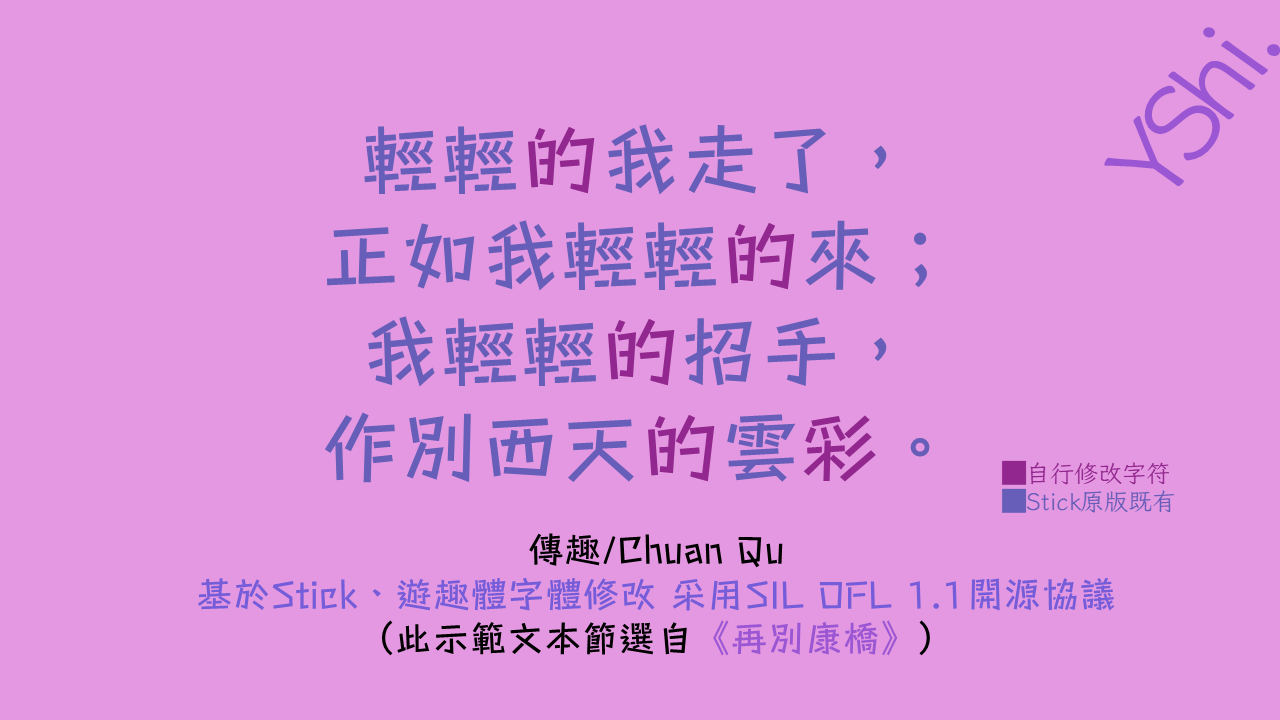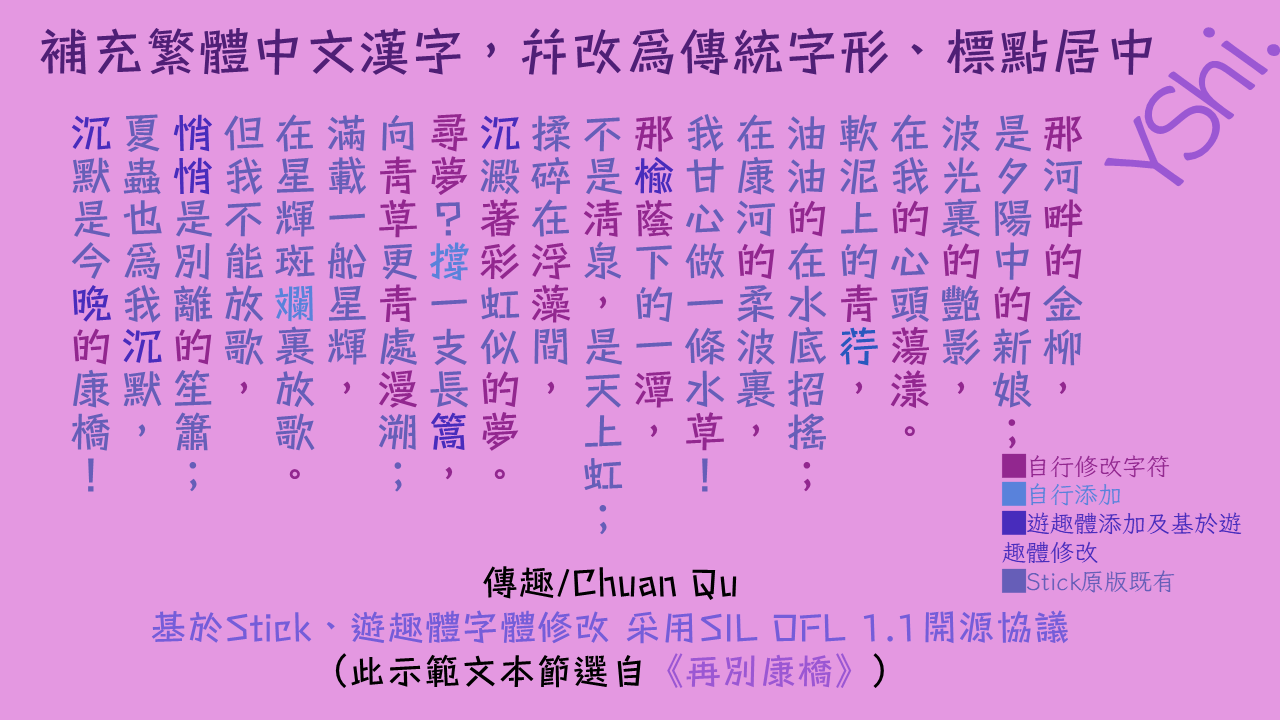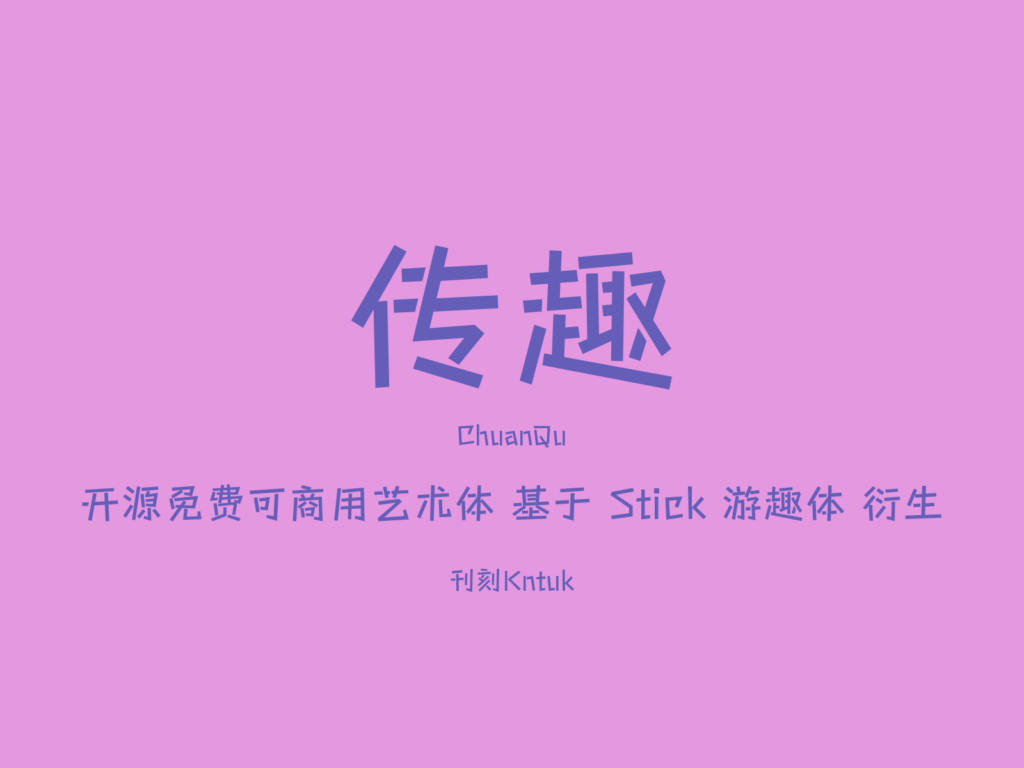
这是一款充满趣味的开源中文字体,其创意灵感源自经典的英文字体 Stick 与国内广受欢迎的中文字体「游趣体」。这款字体在设计和衍生过程中,特别注重融入旧字形元素,使得整体字形散发出一种既俏皮可爱,又带有几分复古韵味的独特风格。Stick 字体最初以其笔直、简洁的线条设计而闻名,这种模仿笔杆形态的直线条,赋予了字体一种天真调皮的性格,同时也营造出一种宁静的田园诗意感,仿佛能让人联想到手写涂鸦或乡村生活的闲适氛围。 由于原版的 Stick 字体主要针对拉丁字母设计,支持的汉字字形数量非常有限,难以满足日常中文书写、排版和设计工作的实际需求。为了解决这一问题,国内的设计师们创作了简体中文版的「游趣体」,极大地扩展了字体的字符集。然而,「游趣体」主要基于现代简化字形,对于追求传统书写美感和特定设计风格的爱好者而言,仍有所缺憾。 因此,出于对旧字形美感的欣赏和对完整字体功能的需求,我发起了这个开源项目。这个项目的核心目标,正是将「游趣体」现有的可爱风格与旧字形进行深度融合。我不仅为字体补充了大量的繁体汉字,使其能够同时适用于简体中文和繁体中文环境,更重要的是,我将许多字形的细节进行了调整,改用更接近传承字形或旧字形的写法,例如保留一些传统笔画结构和部件写法。这样做的目的,是希望创造出一款既能满足现代设计中追求活泼、可爱视觉效果的需求,又能承载传统汉字文化韵味和细节之美的字体,让它在用于标题、海报、插图或品牌标识时,能够增添一份独特的文化温度和亲切感。